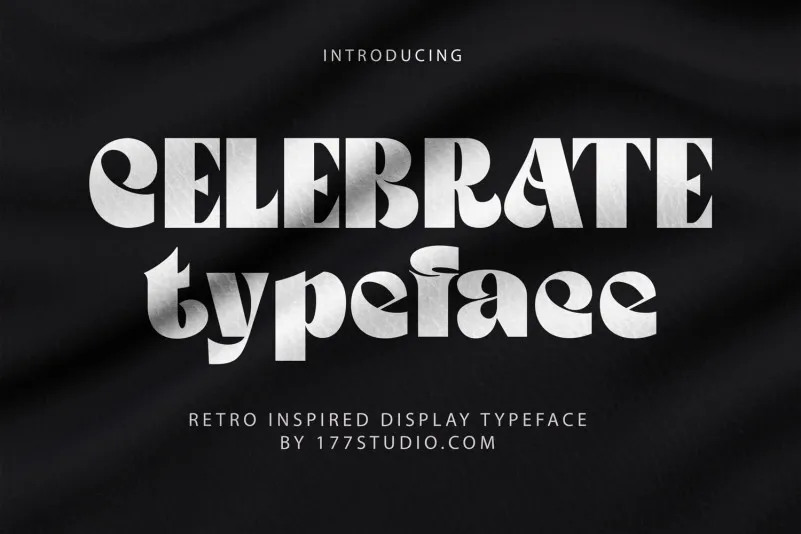
A fonte ‘Celebrate Font’ é uma excelente escolha para quem quer dar um toque retro ao seu design visual, mas com um enfoque mais contemporâneo e moderno. Inspirada nos anos 70 e 80, esta fonte retrogama apresenta um design único que combina a nostalgia do passado com a elegância do presente. Perfeita para logotipos, headlines pesados ou até mesmo para rótulos de cervejas, esta fonte vai deixar seu produto se destacar em meio à multidão. Com uma gama completa e extensa de características, ‘Celebrate Font’ é um dos recursos indispensáveis para qualquer designer que procura manter-se atualizado e criativo na área da tipografia. Seja você criando um design minimalista ou experimentando o excesso com headlines coloridos, esta fonte garante o impacto desejado em qualquer projeto.